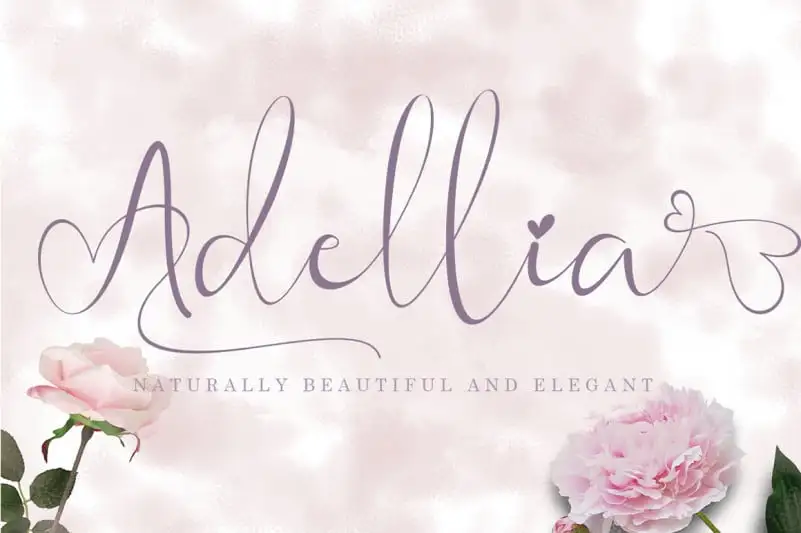
Adellia Calligraphy Font
Esta fonte chamada Adellia Calligraphy Font é uma seleção perfeita para quem busca elegância e beleza no design. Idealmente projetada para tornar qualquer trabalho mais atraente, essa fonte carrega um toque romântico que cria uma impressão única e de alta qualidade. É especialmente indicada para designs em casamentos, identidade visual corporativa, convites, assinaturas, rótulos, logotipos, campanhas promocionais da sua empresa ou até mesmo status no seu feed nas redes sociais. Adellia não é apenas uma fonte; ela é um complemento que enriquece qualquer projeto com uma dose de sofisticação e criatividade. Compostas cuidadosamente para capturar nuances e detalhes, essas letras são perfeitas para expressar suas ideias de maneira elegante e profissional. Em um mundo cada vez mais digital, Adellia oferece a oportunidade de trazer um toque autêntico e personalizado aos seus materiais de marketing e design. O Designer Yoga Letter criou uma fonte que não apenas é linda em si mesma, mas também se adapta perfeitamente às necessidades dos designers. Tanto os iniciantes quanto aqueles que buscam estilos mais elaborados podem encontrar nas linhas suaves e elegantes da Adellia Calligraphy Font a solução ideal para seus projetos.